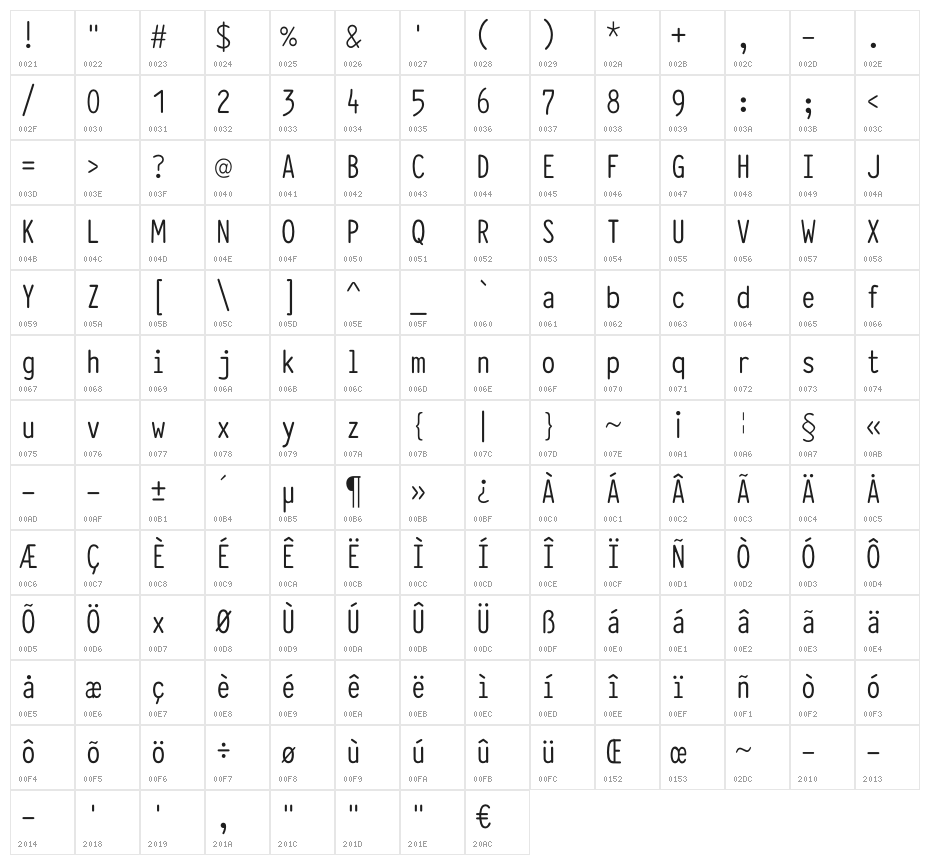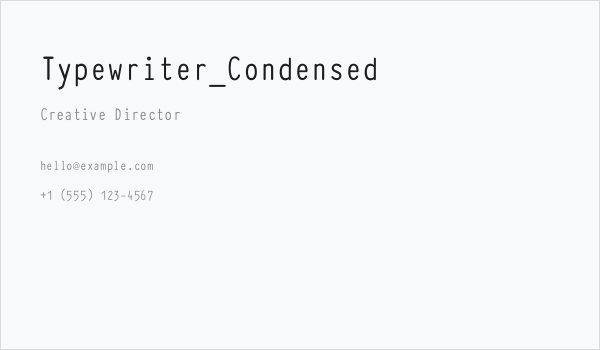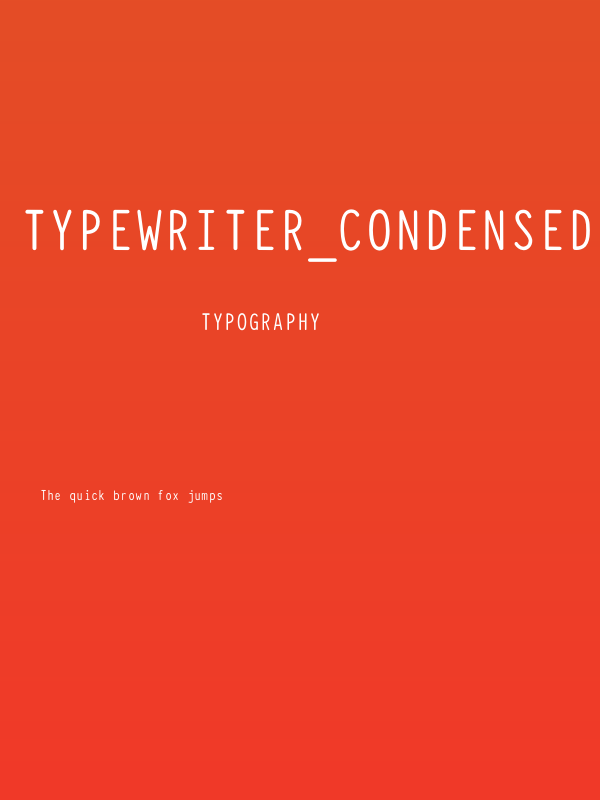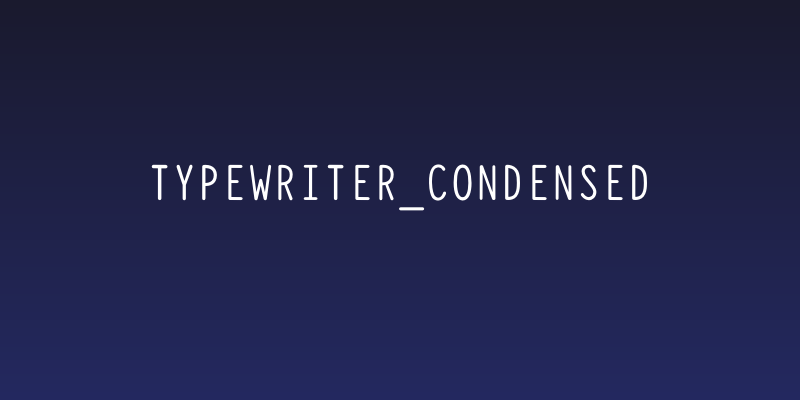
Typewriter_Condensed Font
| श्रेणियाँ | Typewriter |
| चौड़ाई | Condensed |
| अक्षर अंतराल | Normal |
| समग्र शैली | Vintage |
| उपयोग का मामला | Technical documents, Coding, Retro designs |
| सुझाए गए प्रोजेक्ट | Ideal for coding environments, retro-themed designs, technical documents, and any project requiring a vintage typewriter aesthetic. |
| तय पिच है | Yes |